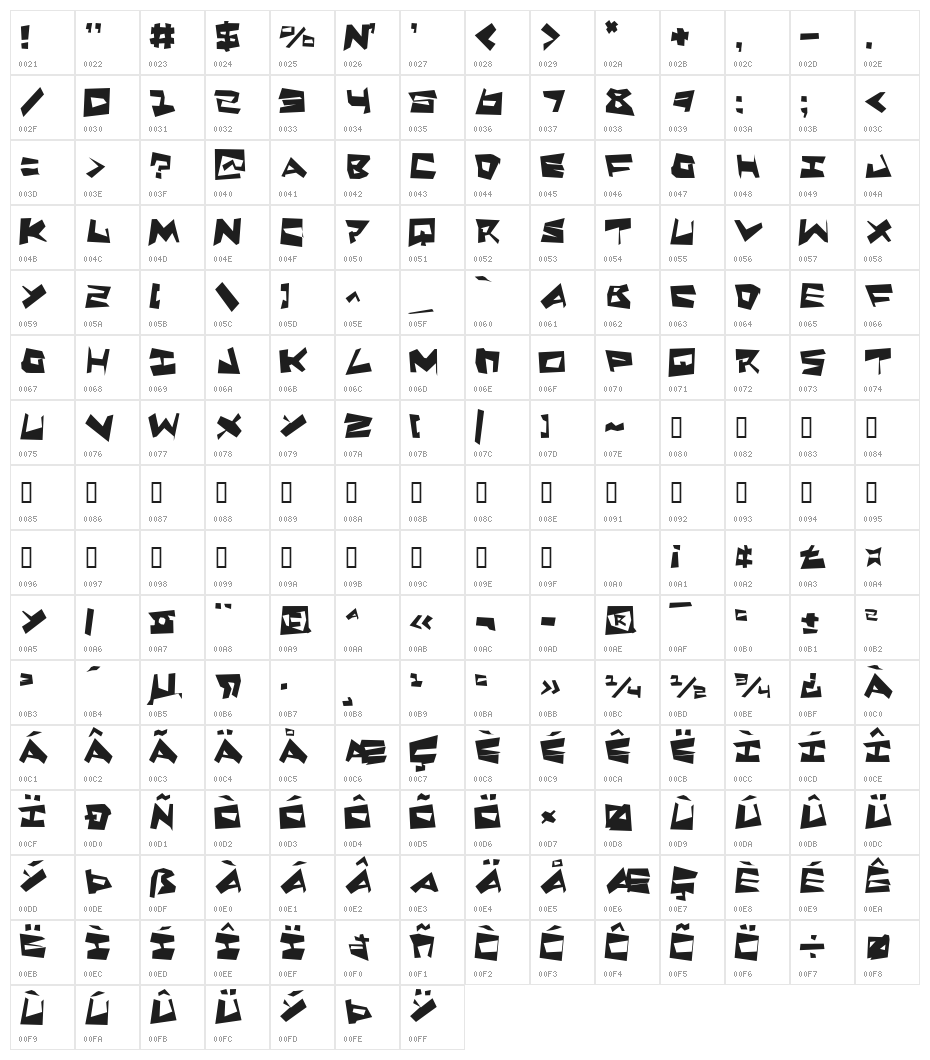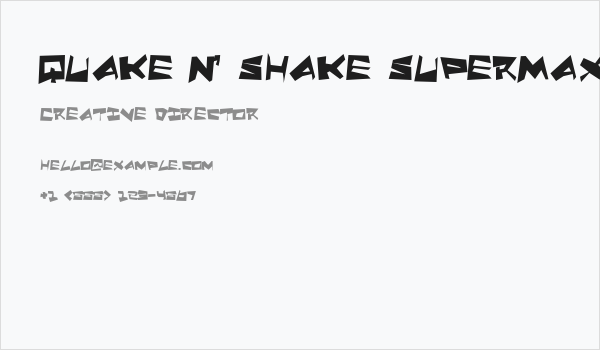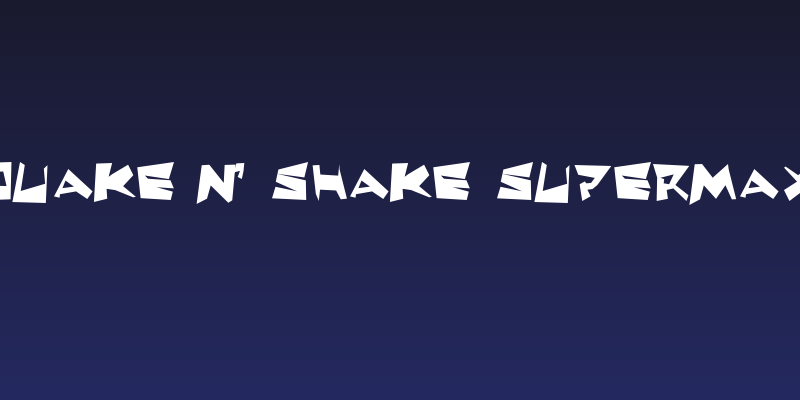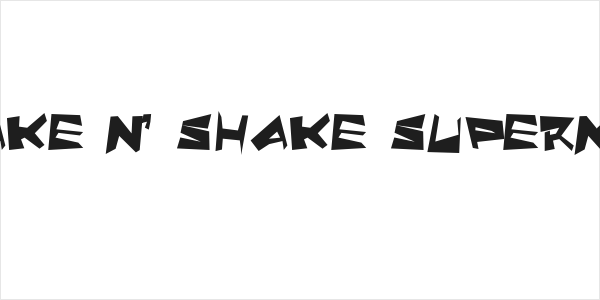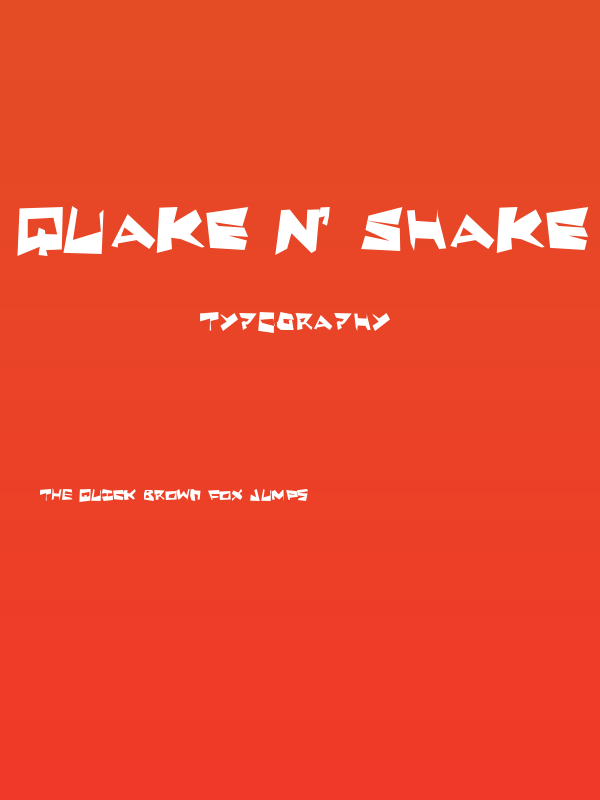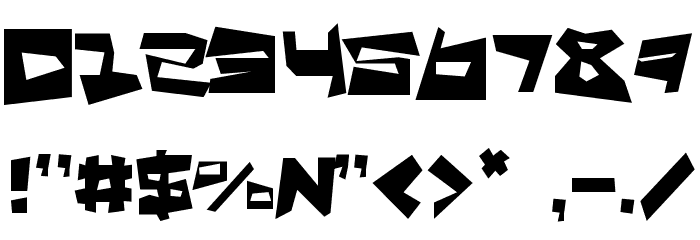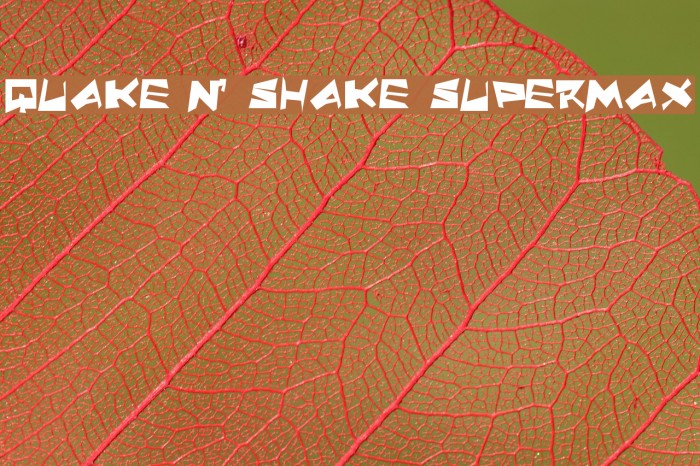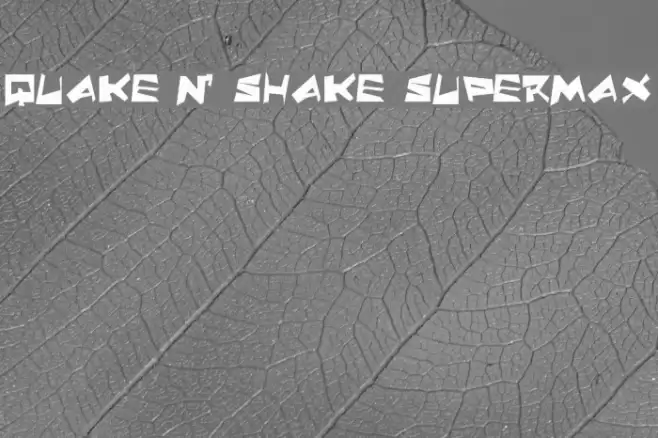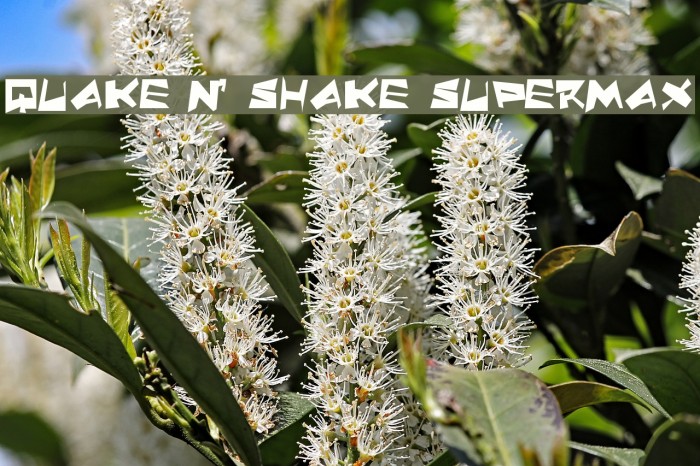
Quake & Shake SuperMax Font
| おすすめプロジェクト | Ideal for projects that require a strong visual impact, such as posters, video game graphics, or branding for edgy and modern products. |